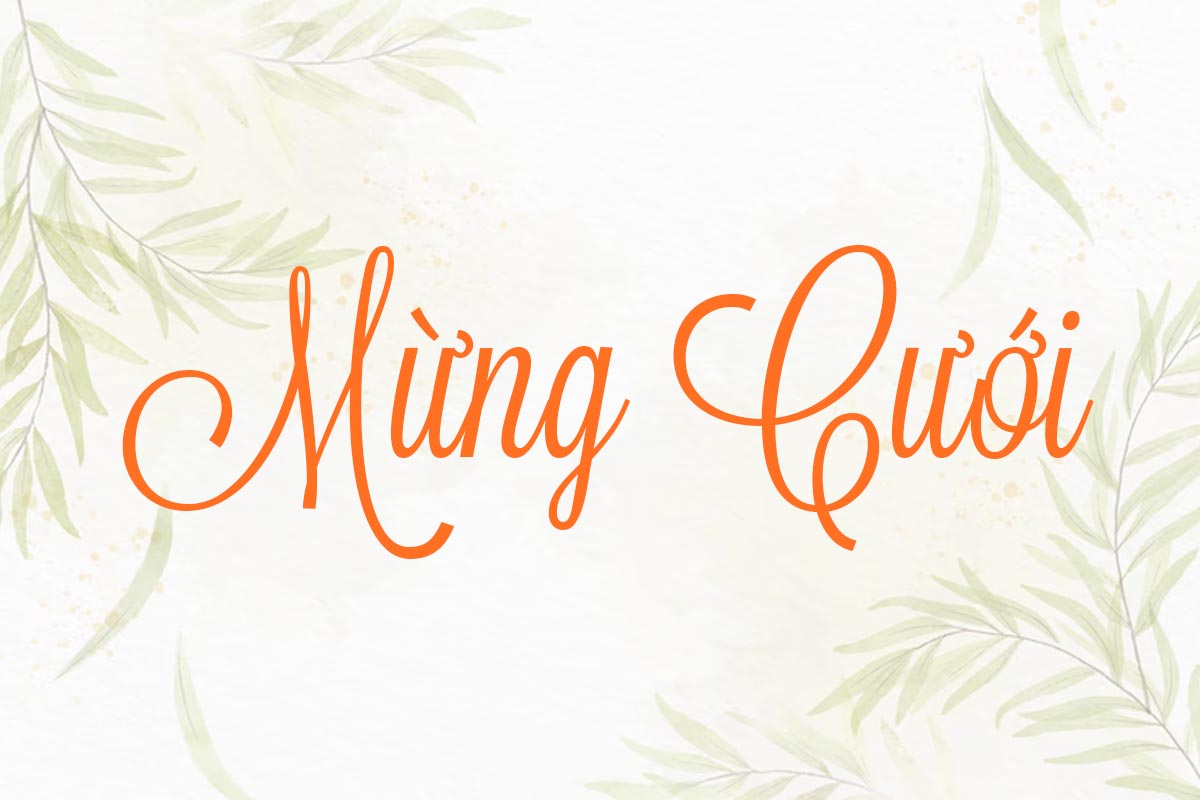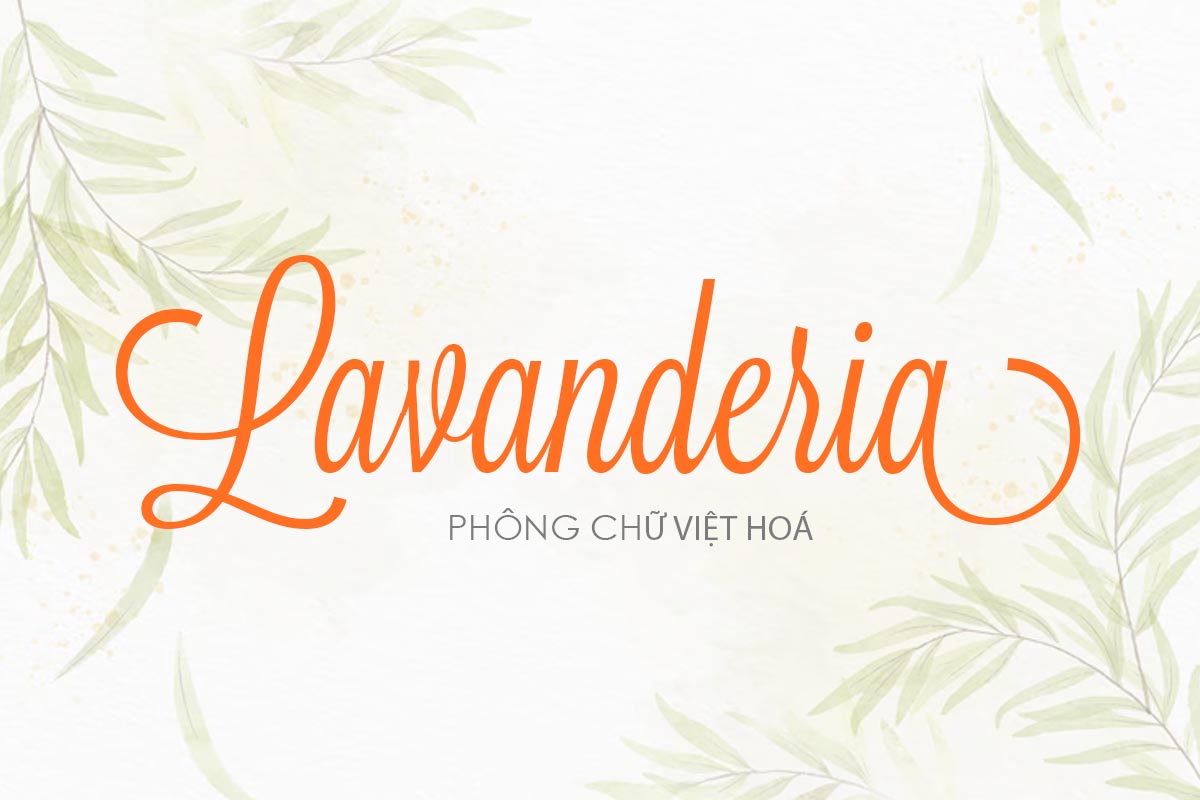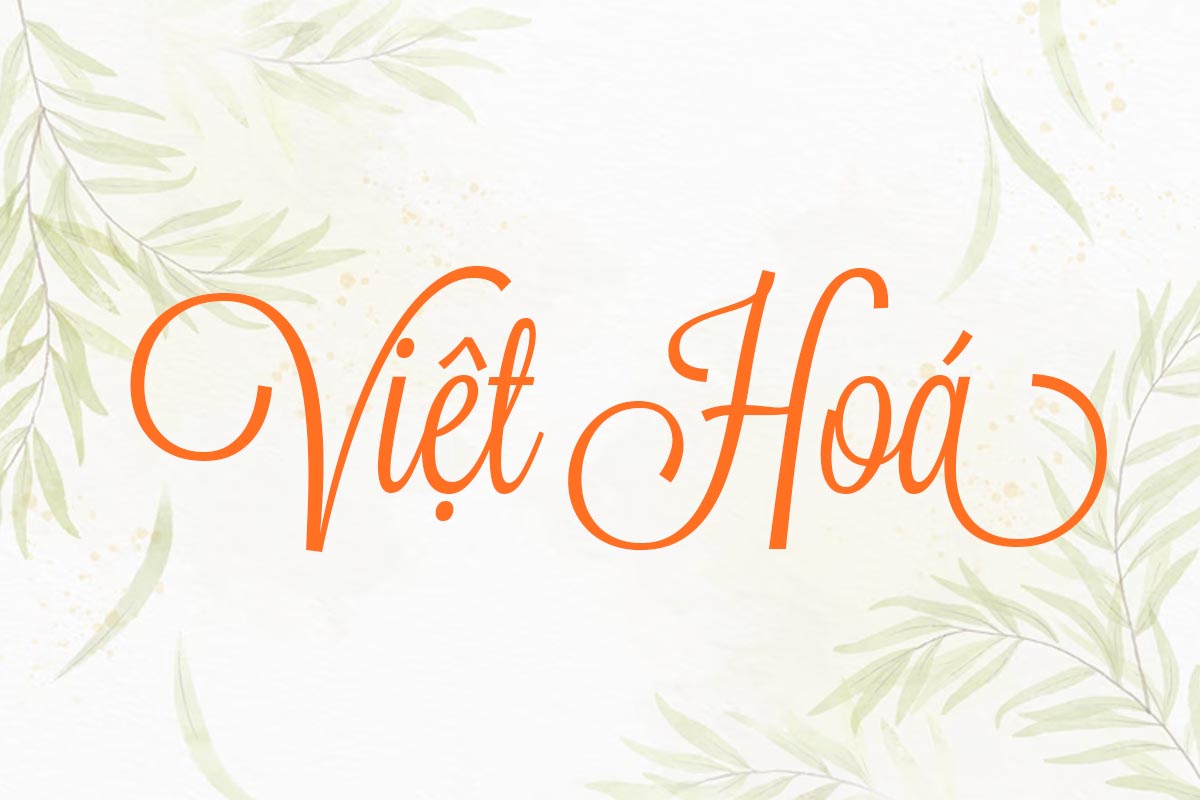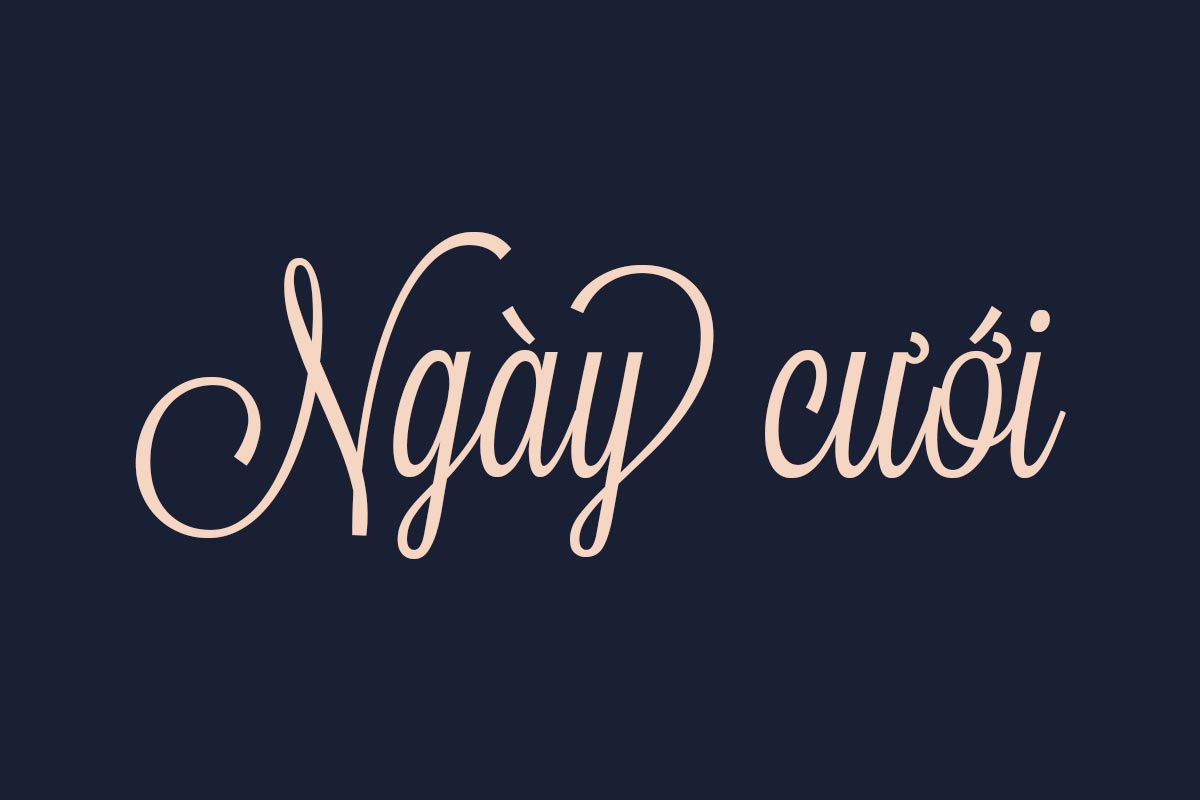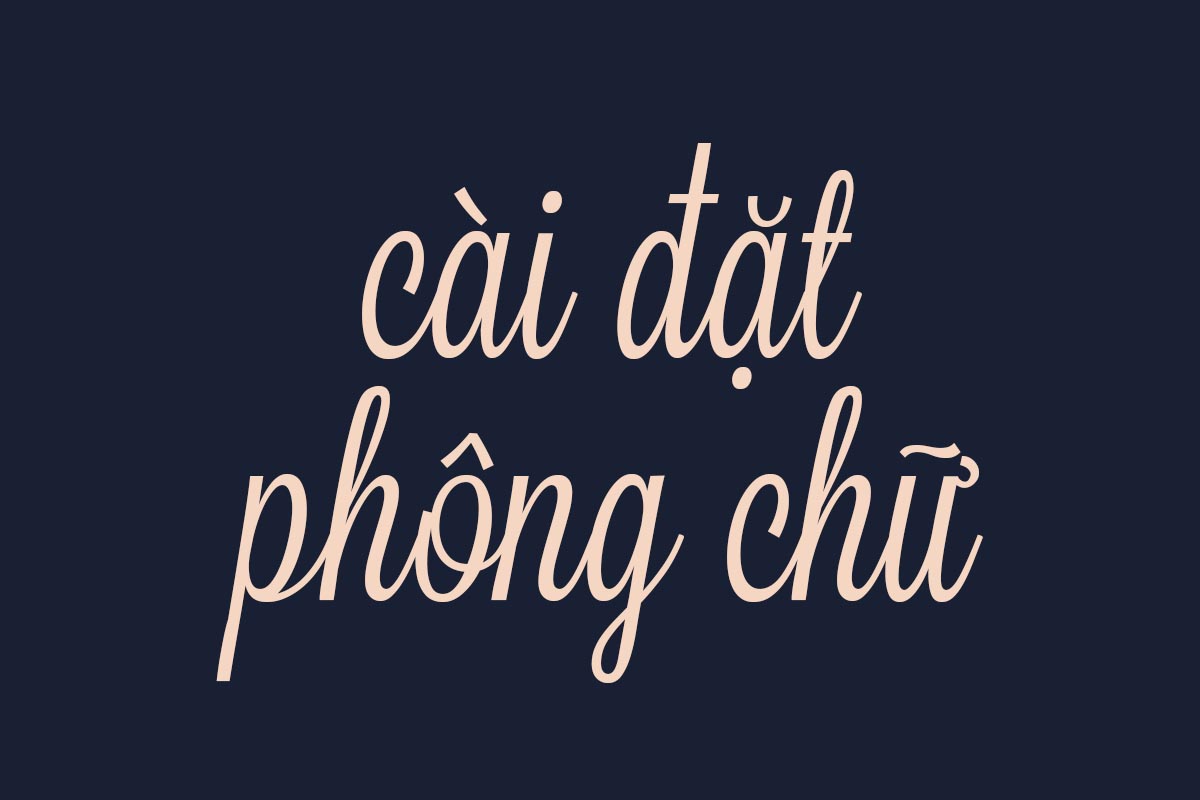
Bạn đang tìm kiếm một font chữ viết tay mềm mại, lãng mạn, phù hợp cho các thiết kế thiệp cưới, thư tay hay tiêu đề ấn tượng? UVF Lavanderia Việt hoá là một trong những lựa chọn hoàn hảo dành cho bạn. Được Việt hoá từ bản gốc nổi tiếng “Lavanderia” bởi James T. Edmondson, phiên bản UVF Lavanderia hỗ trợ đầy đủ dấu tiếng Việt, phù hợp với người dùng Việt Nam. Cái tên “UVF” là viết tắt của “Unicode Vietnamese Font” – một dấu hiệu nhận diện các bộ font đã được Việt hoá toàn diện.
UVF Lavanderia mang phong cách script viết tay cổ điển, đường nét uốn lượn mềm mại và có độ nghiêng nhất định. Kiểu chữ mang hơi hướng retro nhưng không mất đi tính hiện đại, rất phù hợp cho những thiết kế thiên về cảm xúc và sự thanh lịch. Font này có nhiều phiên bản: Lavanderia Regular, Lavanderia Italic, Lavanderia Bold,... tùy theo phiên bản Việt hoá bạn tải. Font có khoảng cách chữ vừa phải, độ cong nhẹ, tạo cảm giác nhẹ nhàng nhưng rõ ràng.
Một trong những lý do font UVF Lavanderia trở nên phổ biến chính là khả năng hỗ trợ đầy đủ tiếng Việt. Các ký tự có dấu như ă, â, ê, ô, đ, ư,… được thiết kế hài hòa với tổng thể font. Dấu thanh (sắc, huyền, hỏi, ngã, nặng) có tỷ lệ và vị trí đặt hợp lý, không gây rối mắt hay đứt mạch thiết kế. Font không lỗi khi dùng trên trình xử lý văn bản, Canva hoặc CapCut.
Thiết kế thiệp cưới, thư tay, tiêu đề blog, trích dẫn truyền cảm hứng
Áp phích phim, bìa sách, bao bì mỹ phẩm handmade
Việc sử dụng Lavanderia giúp bản thiết kế thêm phần cảm xúc, thể hiện sự chỉn chu trong từng nét chữ.
Nếu bạn đang tìm kiếm một font viết tay mềm mại, nhẹ nhàng, giàu cảm xúc – UVF Lavanderia hoàn toàn phù hợp.
Dành cho người thiết kế yêu thích sự cổ điển nhưng hiện đại, muốn tạo ra những sản phẩm thiết kế ấm áp, gần gũi.
→ Là font script, cụ thể là “formal script” lấy cảm hứng từ chữ viết tay bảng hiệu cũ.
→ Có, nếu bạn muốn logo mang tính nghệ thuật, thủ công. Tuy nhiên, với các thương hiệu công nghệ hoặc tối giản thì không phù hợp.